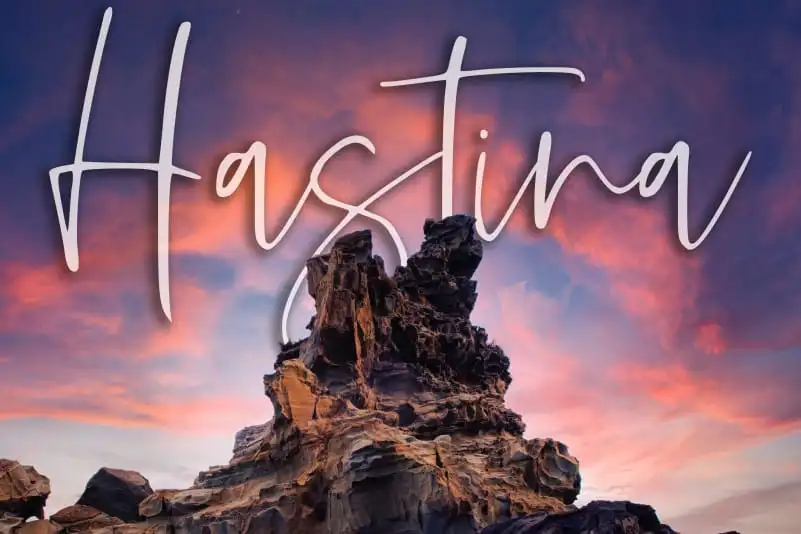
Hastina Script Font – Download Grátis
Hastina Script é uma fonte escrita a mão que transmite elegância e fluidez através dos traços leves e fluidos. Seu design perfeito para invocações de casamento, cartões de agradecimento, frases, cartas de saudação, logotipos e cartões de negócios, proporciona um toque handwritten que torna qualquer projeto singular e memorável. Perfeita tanto para designers como para pessoas comuns criando seus próprios projetos pessoais ou profissionais, Hastina Script oferece uma variedade notável de linhas no ponto final, garantindo que cada letra seja única e convidativa. Além disso, o conjunto completo de alternativas altamente estilizadas torna esta fonte ainda mais versátil para qualquer tipo de projeto, mantendo sempre uma aparência elegante mesmo em formatos diferentes. Com sua graça e versatilidade, Hastina Script é uma escolha óbvia para designers buscando incorporar um toque handwritten perfeito aos seus projetos. Com o designer Genarastudio ao seu lado, você pode ter certeza de que a qualidade da font está em boas mãos.